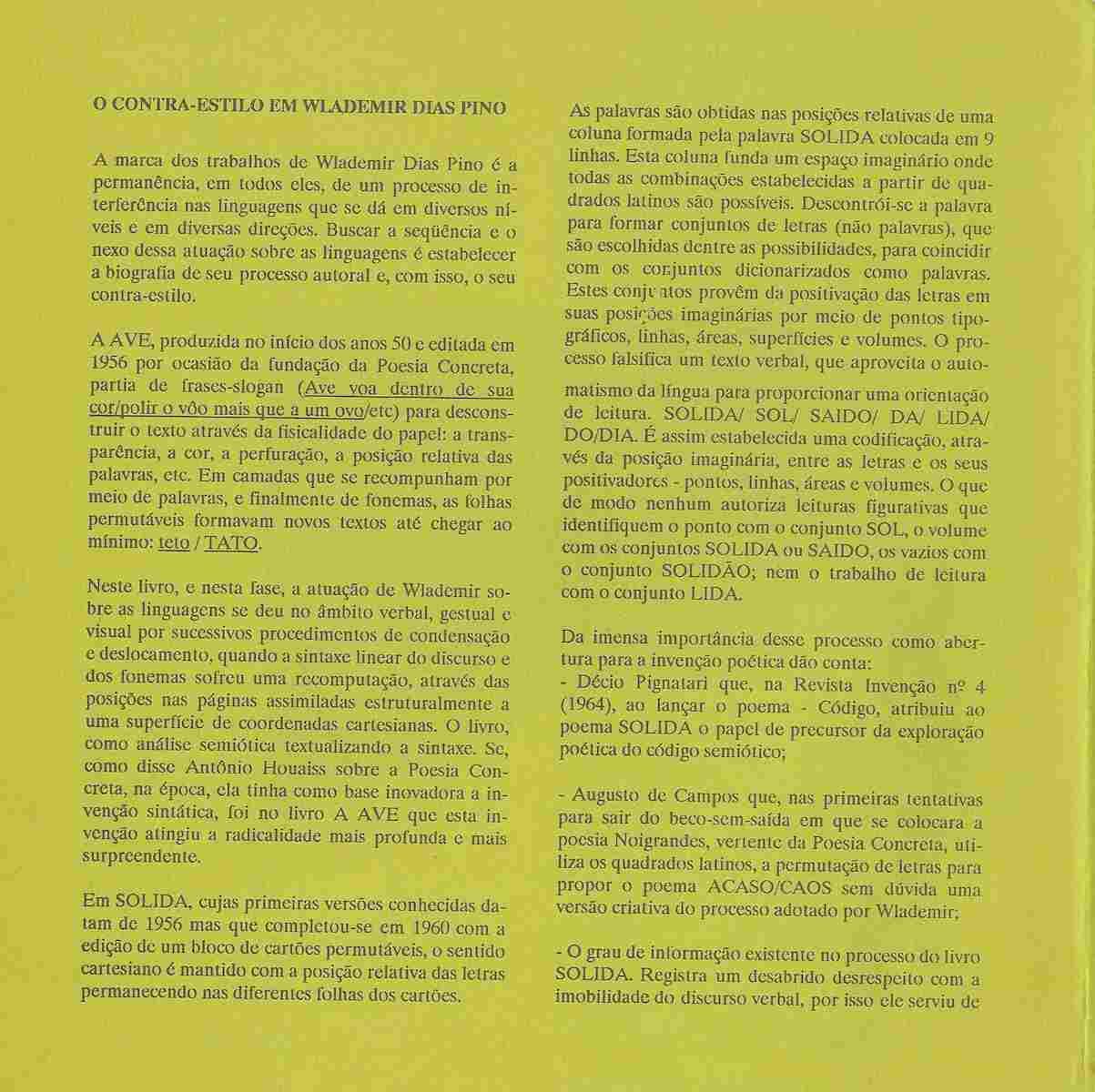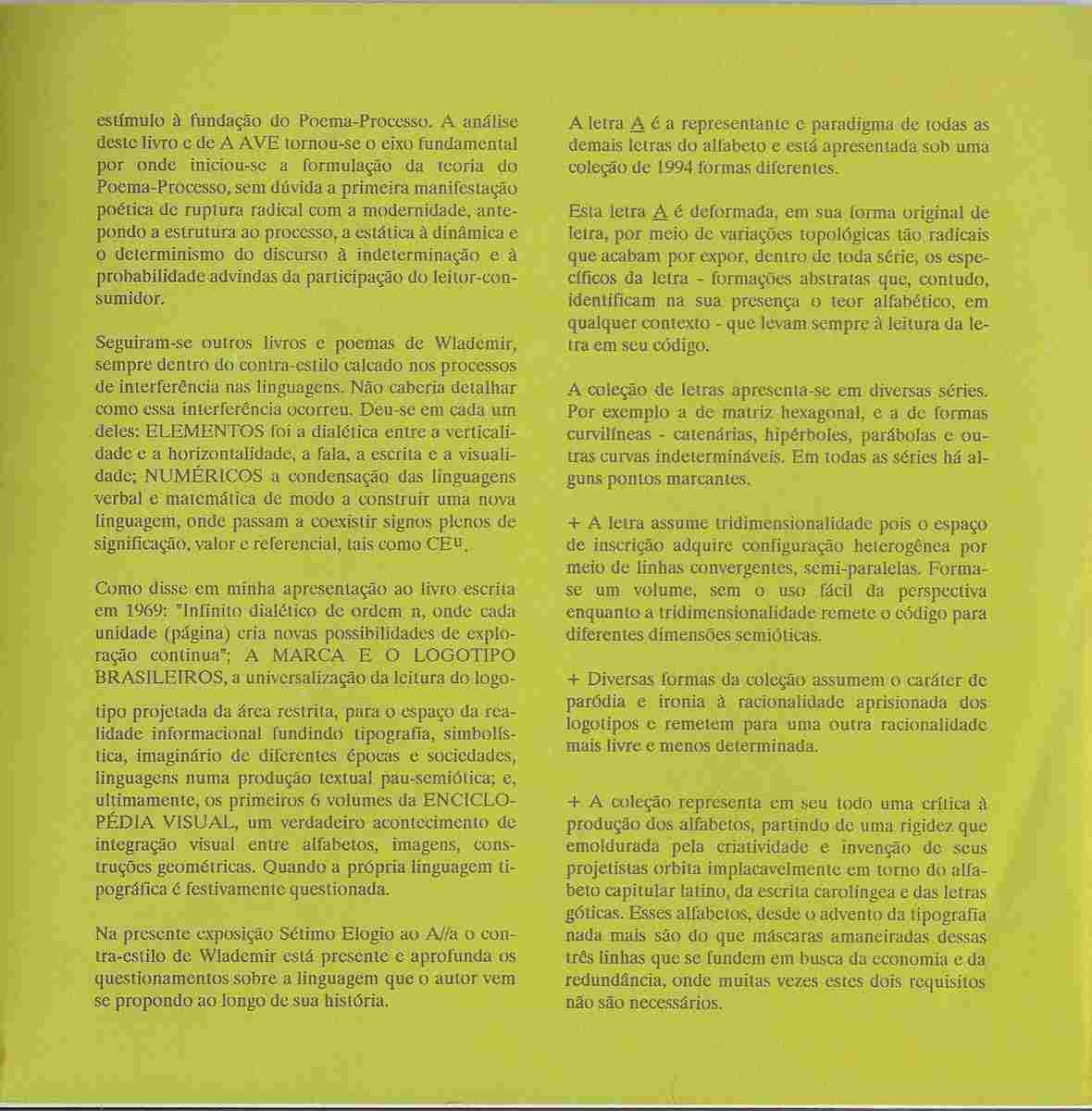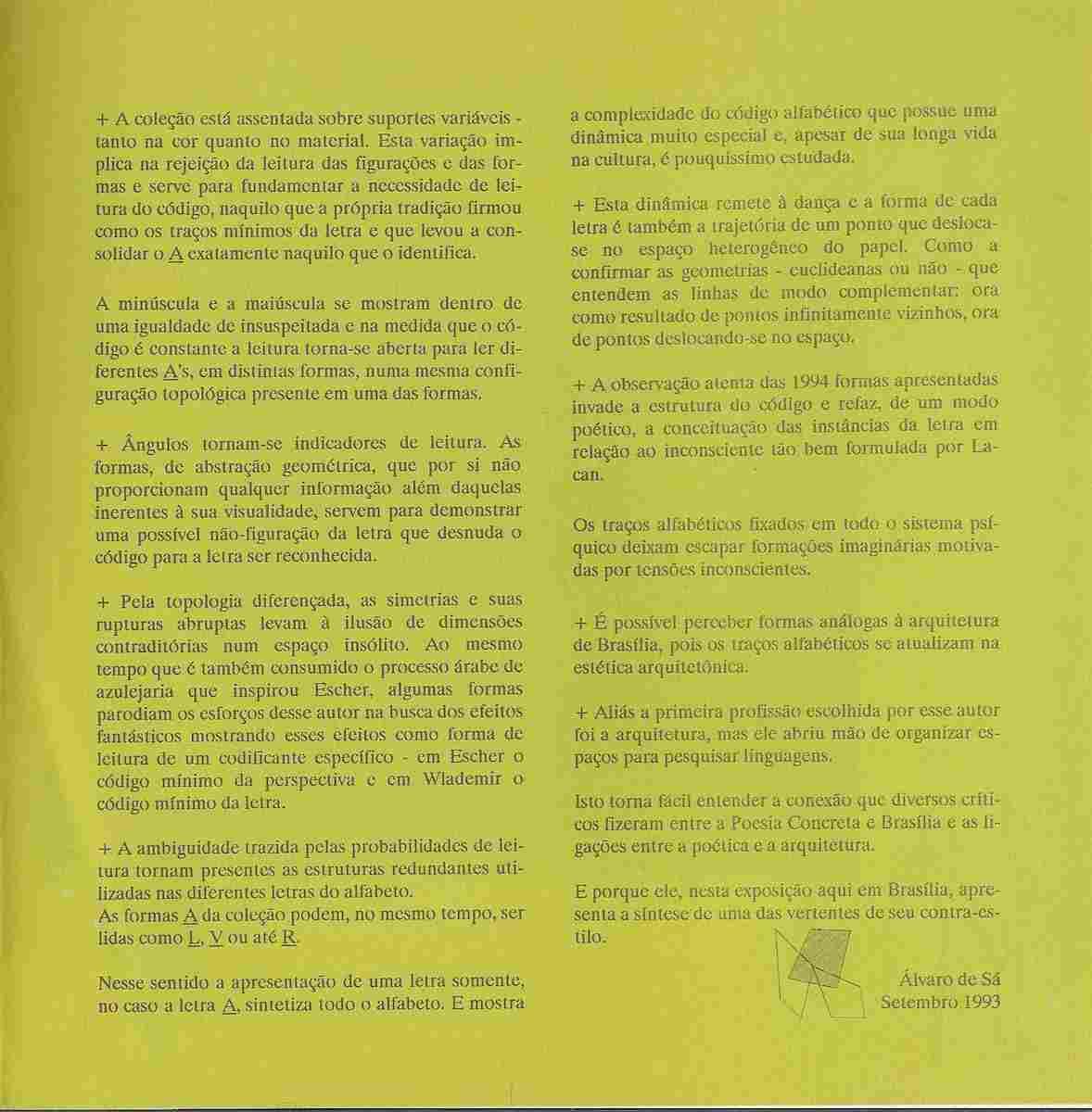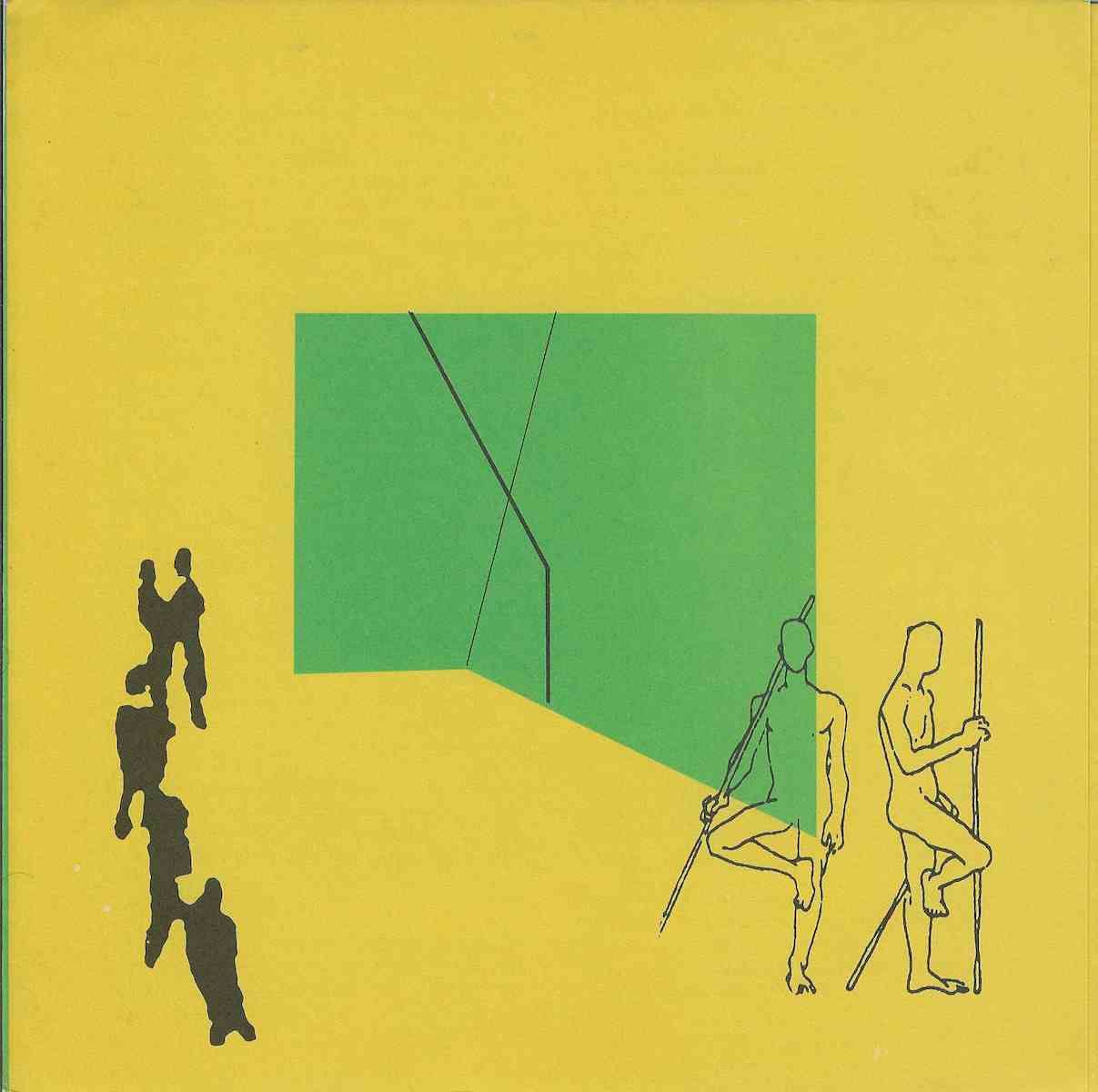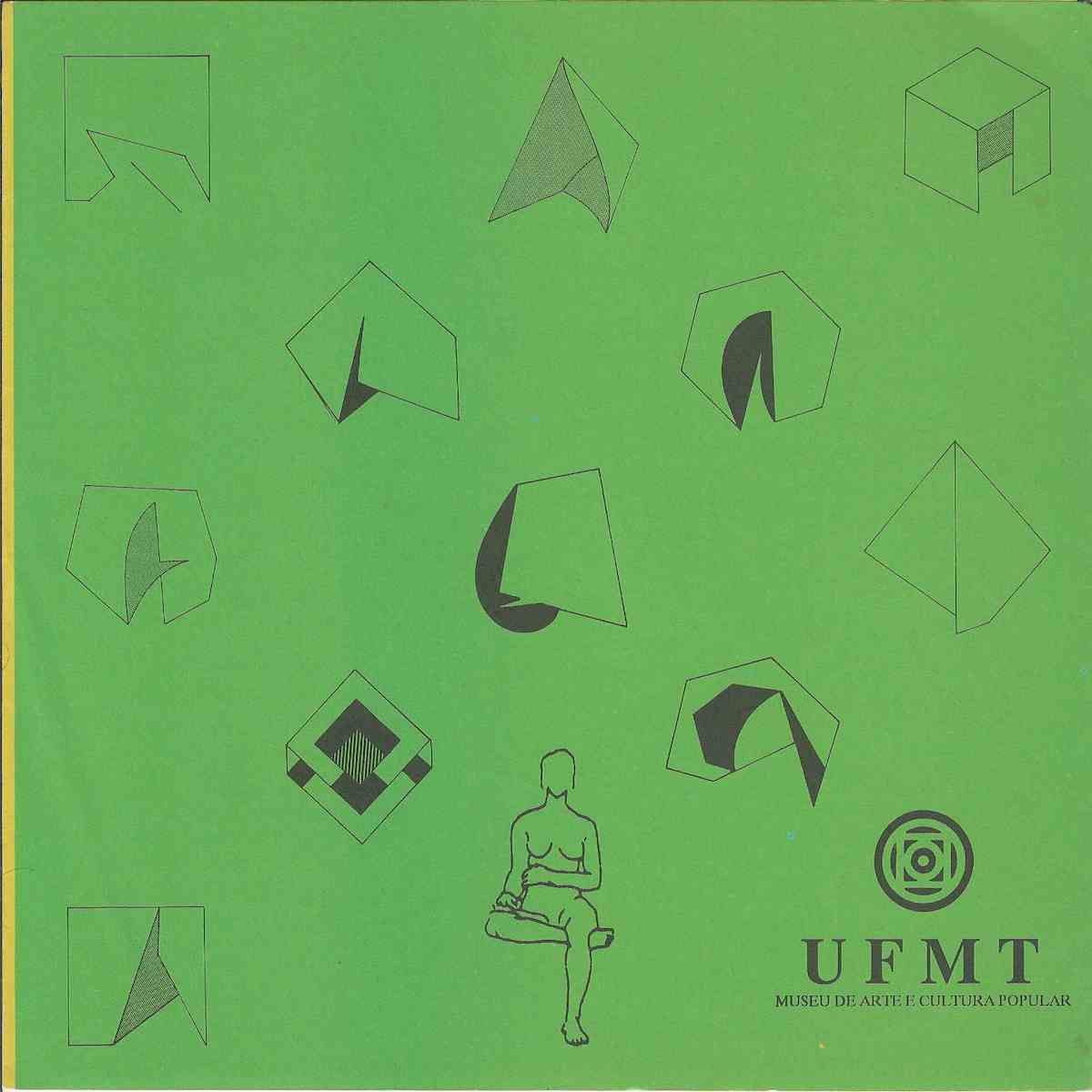
Wlademir Dias Pino, O Contraestilo em Wlademir Dias Pino, setembro de 1993. Conjunto documental e gráfico relacionado às pesquisas de Wlademir Dias Pino sobre poesia visual, linguagem, alfabeto, tipografia, semiótica, espaço, arquitetura e transformação da letra.
Wlademir Dias Pino
Texto para o programa SalsaWlademir Dias Pino, O Contraestilo em Wlademir Dias Pino, setembro de 1993. Conjunto documental e gráfico relacionado às pesquisas de Wlademir Dias Pino sobre poesia visual, linguagem, alfabeto, tipografia, semiótica, espaço, arquitetura e transformação da letra. O núcleo teórico do material é um ensaio de Álvaro de Sá, assinado em setembro de 1993, no qual o autor examina a trajetória de Wlademir Dias Pino a partir do conceito de contraestilo. O conjunto inclui ainda estudos gráficos e espaciais da letra A, figuras humanas, estruturas geométricas e a identificação institucional da UFMT e do Museu de Arte e Cultura Popular.Álvaro de Sá inicia o ensaio afirmando que uma característica permanente dos trabalhos de Wlademir Dias Pino é o processo de interferência nas linguagens, realizado em diferentes níveis e direções. Para o autor, acompanhar essa sequência de interferências permite estabelecer uma biografia do processo autoral de Wlademir e, simultaneamente, compreender a formação de seu contraestilo. Assim, a produção de Wlademir Dias Pino não é apresentada como repetição de uma fórmula visual estável, mas como permanente investigação e transformação dos sistemas de linguagem.O texto dedica atenção especial a A Ave, produzida no início da década de 1950 e editada em 1956. Segundo Álvaro de Sá, o livro parte de frases e estruturas verbais para progressivamente desconstruir o texto por meio da fisicalidade do papel, da transparência, da cor, da perfuração, da posição relativa das palavras e da sobreposição de diferentes camadas. As folhas permutáveis recompõem novos textos e conduzem a obra em direção a unidades cada vez menores, chegando aos fonemas e a relações mínimas entre elementos verbais e sensoriais.A Ave é apresentada como uma experiência na qual a linguagem verbal, gestual e visual é submetida a sucessivos procedimentos de condensação e deslocamento. A sintaxe linear do discurso e dos fonemas sofre uma recomputação através da disposição espacial das páginas, assimiladas a uma superfície de coordenadas cartesianas. Álvaro de Sá aproxima esse procedimento de uma análise semiótica que transforma a própria sintaxe em objeto de investigação.O ensaio menciona Antônio Houaiss e sua avaliação da inovação sintática da Poesia Concreta, observando que A Ave teria levado essa investigação a uma radicalidade ainda mais profunda. O documento insere, portanto, o livro de Wlademir Dias Pino no centro das discussões sobre poesia concreta, poesia visual e transformação da sintaxe poética na segunda metade do século XX.Outro trabalho fundamental analisado é SOLIDA. Segundo o ensaio, suas primeiras versões conhecidas datam de 1956 e o projeto teria sido completado em 1960 com a edição de um bloco de cartões permutáveis. O sentido cartesiano permanece através da posição relativa das letras distribuídas pelas diferentes folhas ou cartões.Em SOLIDA, palavras são obtidas a partir das posições relativas de uma coluna formada pela palavra SOLIDA disposta em diferentes linhas. A estrutura cria um espaço imaginário no qual diversas combinações derivadas de quadrados latinos podem ser realizadas. O processo desconstrói a palavra para produzir conjuntos de letras e não necessariamente palavras convencionais. Esses conjuntos são selecionados entre as possibilidades combinatórias e podem coincidir com formas reconhecidas pelo dicionário.Segundo Álvaro de Sá, esses conjuntos derivam do posicionamento das letras em relações imaginárias estabelecidas por pontos tipográficos, linhas, áreas, superfícies e volumes. O processo constrói uma espécie de texto verbal transformado, aproveitando o automatismo da língua para oferecer uma orientação de leitura sem restringir a experiência a uma única interpretação.O ensaio cita sequências derivadas de SOLIDA e explica que o método estabelece uma codificação através da posição imaginária das letras e de seus elementos estruturais. Ao mesmo tempo, o autor alerta que isso não autoriza uma leitura simplesmente figurativa. Um ponto não deve ser automaticamente identificado com determinado conjunto verbal, nem um volume com outro. A operação fundamental encontra se no funcionamento do sistema e na mobilidade das possibilidades de leitura.Álvaro de Sá destaca a importância desse processo para a invenção poética e recorda a recepção de SOLIDA no contexto da poesia experimental brasileira. O texto menciona Décio Pignatari e a revista Invenção número 4, de 1964, registrando que Pignatari, ao apresentar o poema Código, atribuiu a SOLIDA um papel precursor na exploração poética do código semiótico.O ensaio também menciona Augusto de Campos. Segundo Álvaro de Sá, experiências de permutação de letras desenvolvidas por Augusto de Campos para o poema ACASO CAOS poderiam ser relacionadas criativamente ao procedimento anteriormente desenvolvido por Wlademir Dias Pino em SOLIDA. A comparação situa a obra dentro de um campo mais amplo de poesia combinatória, permutacional e semiótica.Para Álvaro de Sá, o nível de informação contido no processo de SOLIDA representa uma ruptura com a imobilidade do discurso verbal e teria contribuído para o caminho que desembocaria na formulação teórica do Poema Processo. A análise de A Ave e SOLIDA é apresentada como eixo fundamental para compreender a passagem da escritura ao processo, do estático ao dinâmico, do determinismo à indeterminação e à participação ativa do leitor consumidor.O texto estabelece dessa forma uma genealogia direta entre as pesquisas de Wlademir Dias Pino realizadas nas décadas de 1950 e 1960 e o surgimento do Poema Processo. A obra deixa de ser entendida apenas como objeto verbal concluído e passa a ser concebida como sistema aberto, procedimento, matriz de possibilidades e experiência de participação.Álvaro de Sá menciona outros livros e projetos de Wlademir Dias Pino que continuaram essa interferência nas linguagens. ELEMENTOS é associado à dialética entre verticalidade e horizontalidade e às relações entre fala, escrita e visualidade. NUMÉRICOS é relacionado à condensação das linguagens verbal e matemática, construindo uma nova linguagem na qual podem coexistir signos dotados de significado, valor e referência.O texto recupera ainda uma apresentação realizada por Álvaro de Sá ao livro Escrita em 1969, na qual destacava a estrutura dialética da página como unidade capaz de gerar novas possibilidades contínuas de exploração.Entre outras etapas da trajetória de Wlademir Dias Pino, o ensaio menciona A MARCA E O LOGOTIPO BRASILEIROS, associando o projeto à universalização da leitura do logotipo e ao estudo da realidade informacional. A pesquisa reúne tipografia, simbologia e imaginário de diferentes épocas e sociedades em uma produção textual e semiótica.Também são citados os seis primeiros volumes da ENCICLOPÉDIA VISUAL, apresentados como acontecimento de integração entre alfabetos, imagens e construções geométricas. Nesse conjunto, a própria linguagem tipográfica passa a ser sistematicamente interrogada.Essas diferentes experiências convergem na exposição identificada no texto como Sétimo Elogio ao A/a. Álvaro de Sá afirma que o contraestilo de Wlademir está presente nessa exposição e aprofunda questionamentos sobre a linguagem que o artista vinha desenvolvendo ao longo de sua trajetória.A letra A é escolhida como representante e paradigma das demais letras do alfabeto e, segundo o ensaio, é apresentada sob uma coleção de formas diferentes. O A deixa de ser apenas caractere tipográfico e passa a constituir uma matriz de variações topológicas, espaciais e semióticas.A letra é deformada a partir de sua configuração original por variações topológicas não radicais que acabam expondo diferentes aspectos de sua estrutura. Mesmo quando as formas se tornam abstratas, elas mantêm sinais suficientes para permitir o reconhecimento de um conteúdo alfabético e conduzir novamente à leitura da letra dentro do código.A coleção apresenta diferentes séries. O texto menciona, entre elas, uma matriz hexagonal e séries de formas curvilíneas, incluindo catenárias, hipérboles, parábolas e outras curvas de desenvolvimento potencialmente indeterminado.Álvaro de Sá destaca que a letra adquire tridimensionalidade. O espaço de inscrição passa a assumir uma configuração heterogênea através de linhas convergentes e não paralelas. Forma se um volume sem recorrer ao uso fácil da perspectiva, ao mesmo tempo em que a tridimensionalidade transporta o código para diferentes dimensões semióticas.A coleção possui também dimensão de paródia e ironia em relação à racionalidade rígida dos logotipos. Para o autor, determinadas formas remetem a uma racionalidade mais livre e menos determinada. A pesquisa deixa de ser apenas tipográfica e se transforma em crítica aos mecanismos históricos de padronização do alfabeto.Álvaro de Sá observa que a produção dos alfabetos esteve cercada, ao longo do tempo, por uma rigidez ligada à escrita carolíngia e às letras góticas. Em sua interpretação, muitos desses alfabetos representam máscaras estilizadas das linhas fundamentais que constituem as letras, e a pesquisa de Wlademir procura revelar as estruturas mínimas existentes por trás dessas convenções.Outro aspecto importante é a utilização de suportes variáveis, tanto em cor quanto em material. A variação rejeita a ideia da letra como configuração fixa e demonstra a necessidade de releitura do código alfabético. O texto chama atenção para o fato de que a tradição consolidou determinados traços mínimos como elementos suficientes para reconhecer uma letra, especialmente o A, e Wlademir explora exatamente os limites dessa identificação.As versões maiúscula e minúscula da letra são colocadas em relação dinâmica. À medida que o código se abre, a leitura pode reconhecer diferentes As dentro de uma mesma configuração topológica.Algumas formas funcionam como indicadores de leitura. Outras tornam se abstrações geométricas que oferecem inicialmente informações apenas visuais, provocando uma situação de não figuração da letra antes que o código volte a ser reconhecido. Essa tensão entre reconhecimento e estranhamento é central no processo.O ensaio aproxima as construções de Wlademir de certos princípios encontrados na obra de M C Escher e na tradição da azulejaria árabe. Álvaro de Sá ressalta, porém, que existem diferenças essenciais. Em Escher, o elemento mínimo estaria relacionado ao código da perspectiva, enquanto em Wlademir Dias Pino o código mínimo seria a própria letra.A diferenciação topológica e a ruptura de simetrias criam ilusões espaciais e dimensões contraditórias. O alfabeto passa assim a atuar como uma arquitetura de possibilidades perceptivas.As ambiguidades de leitura também fazem com que uma única estrutura possa sugerir diferentes letras. O texto menciona que determinadas formas do A podem simultaneamente ser percebidas como L, V ou até R. A apresentação de uma única letra permite, dessa maneira, sintetizar potencialmente todo o alfabeto.Para Álvaro de Sá, esse procedimento demonstra a complexidade do código alfabético, um sistema dotado de dinâmica particular que, apesar de sua longa presença cultural, ainda seria pouco estudado em sua dimensão visual e estrutural.Essa dinâmica começa a produzir uma espécie de dança das formas. Cada letra corresponde também à trajetória de um ponto deslocando se no espaço heterogêneo do papel. A pesquisa aproxima geometria, movimento, código e percepção.O ensaio observa ainda que as formas apresentadas em 1994 invadem a estrutura do código e permitem uma reflexão poética sobre as relações entre a letra e o inconsciente. Os traços alfabéticos estabilizados dentro do sistema psíquico podem liberar formações imaginárias motivadas por tensões inconscientes.Álvaro de Sá estabelece também uma aproximação entre as formas da pesquisa de Wlademir e a arquitetura de Brasília. Segundo o texto, os traços alfabéticos podem atualizar se dentro da estética arquitetônica. Essa relação entre letra e construção espacial adquire particular importância porque a arquitetura foi uma das práticas profissionais escolhidas por Wlademir Dias Pino e lhe permitiu organizar espaços para investigar linguagens.O ensaio conclui que essa relação ajuda a compreender as conexões apontadas por diversos críticos entre Poesia Concreta e Brasília e entre poética e arquitetura. A exposição realizada em Brasília é apresentada, portanto, como síntese de uma das vertentes do contraestilo de Wlademir Dias Pino.As imagens que acompanham o texto reforçam essa dimensão espacial. Em uma composição, figuras humanas aparecem ao redor de um grande plano verde colocado sobre um campo amarelo, atravessado por linhas que sugerem eixo, profundidade, deslocamento e estrutura. Em outra página, diferentes configurações geométricas e curvilíneas são distribuídas sobre um fundo verde, apresentando variações que podem ser interpretadas simultaneamente como letra, objeto, planta, volume, arquitetura e escultura. A presença da figura humana estabelece escala e sugere o deslocamento da letra do espaço gráfico para o espaço corporal e ambiental.O Contraestilo em Wlademir Dias Pino constitui um documento crítico de grande relevância porque oferece uma interpretação histórica e conceitual da obra de Wlademir Dias Pino escrita por Álvaro de Sá, outro protagonista fundamental do Poema Processo. O texto documenta relações entre A Ave, SOLIDA, ELEMENTOS, NUMÉRICOS, Escrita, A Marca e o Logotipo Brasileiros, Enciclopédia Visual e a exposição Sétimo Elogio ao A/a, formando uma importante cartografia da produção do artista.O documento é especialmente relevante para pesquisas sobre Wlademir Dias Pino, Álvaro de Sá, Poema Processo, Poesia Concreta, A Ave, SOLIDA, poesia visual brasileira, poesia experimental, semiótica, código alfabético, poesia combinatória, livros permutáveis, livro de artista, tipografia experimental, design gráfico, comunicação visual, alfabetos, logotipos, Enciclopédia Visual, arquitetura, Brasília, M C Escher, Décio Pignatari, Augusto de Campos, Antônio Houaiss, revista Invenção, UFMT, Museu de Arte e Cultura Popular e história da vanguarda brasileira.ENGLISHText for the Salsa programWlademir Dias Pino, The Counterstyle in Wlademir Dias Pino, September 1993. Documentary and graphic ensemble related to the investigations of Wlademir Dias Pino into visual poetry, language, alphabet, typography, semiotics, space, architecture and the transformation of letters. The theoretical core of the material is an essay by Álvaro de Sá, signed in September 1993, in which he examines the trajectory of Wlademir Dias Pino through the concept of counterstyle. The ensemble also contains graphic and spatial studies of the letter A, human figures, geometric structures and the institutional identification of UFMT and the Museum of Popular Art and Culture.Álvaro de Sá begins by stating that a permanent characteristic of the work of Wlademir Dias Pino is a process of interference within languages, operating at different levels and in different directions. For the author, following this sequence of interventions makes it possible to establish a biography of the creative process of Wlademir and, simultaneously, to understand the formation of his counterstyle. His production is therefore presented not as the repetition of a stable visual formula but as a continuous investigation and transformation of systems of language.The essay gives particular attention to A Ave, produced in the early 1950s and published in 1956. According to Álvaro de Sá, the book begins with verbal phrases and structures and progressively dismantles the text through the physical properties of paper, transparency, color, perforation, the relative position of words and the superimposition of layers. Permutable sheets reconstruct new texts and lead the work toward increasingly reduced units, eventually reaching phonemes and minimal relationships between verbal and sensory components.A Ave is presented as an experiment in which verbal, gestural and visual language is subjected to successive procedures of condensation and displacement. The linear syntax of discourse and phonemes undergoes a recomputation through the spatial arrangement of pages conceived as a surface of Cartesian coordinates. Álvaro de Sá relates this procedure to a semiotic analysis in which syntax itself becomes the object of investigation.The essay refers to Antônio Houaiss and his assessment of the syntactic innovations of Concrete Poetry, arguing that A Ave carried this investigation toward an even more radical territory. The document consequently places the book by Wlademir Dias Pino at the center of discussions concerning Concrete Poetry, visual poetry and the transformation of poetic syntax during the second half of the twentieth century.Another fundamental work analyzed in the essay is SOLIDA. According to the text, its earliest known versions date from 1956 and the project was completed in 1960 with the publication of a block of permutable cards. A Cartesian principle is maintained through the relative position of letters distributed across the different cards.In SOLIDA, words are generated from the relative positions of a column formed by the word SOLIDA distributed over different lines. This column establishes an imaginary space in which combinations derived from Latin squares become possible. The procedure decomposes the word in order to create sets of letters that are not necessarily conventional words. These sets are selected from the available combinatorial possibilities and may coincide with forms recognized by dictionaries.According to Álvaro de Sá, these combinations derive from the positioning of letters within imaginary relationships constructed through typographic points, lines, areas, surfaces and volumes. The process produces a transformed verbal text that uses the automatic mechanisms of language to suggest orientations of reading without limiting the experience to a single interpretation.The essay explains that the method establishes a codification based on the imaginary positions of letters and their structural elements. At the same time, Álvaro de Sá warns that the system does not authorize a merely figurative reading. A point should not automatically be identified with a particular verbal set, nor should a volume be equated with another set. The essential operation lies in the functioning of the system and in the mobility of possible readings.Álvaro de Sá emphasizes the importance of this process for poetic invention and recalls the reception of SOLIDA within Brazilian experimental poetry. The essay mentions Décio Pignatari and issue number 4 of the magazine Invenção from 1964, recording that Pignatari, when presenting the poem Código, attributed to SOLIDA a pioneering role in the poetic exploration of the semiotic code.The text also refers to Augusto de Campos. According to Álvaro de Sá, experiments with letter permutations developed by Augusto de Campos for the poem ACASO CAOS can be creatively related to procedures previously explored by Wlademir Dias Pino in SOLIDA. This comparison situates the work within a broader field of combinatorial, permutational and semiotic poetry.For Álvaro de Sá, the degree of information contained in the process of SOLIDA represents a challenge to the immobility of verbal discourse and contributed to the path that would lead to the theoretical formulation of Poema Processo. The analysis of A Ave and SOLIDA is presented as fundamental to understanding the movement from writing to process, from the static to the dynamic, from determinism to indeterminacy and to the active participation of the reader consumer.The essay therefore establishes a direct genealogy between the investigations undertaken by Wlademir Dias Pino during the 1950s and 1960s and the emergence of Poema Processo. The work ceases to be understood merely as a completed verbal object and becomes an open system, a procedure, a matrix of possibilities and an experience of participation.Álvaro de Sá refers to other books and projects by Wlademir Dias Pino that continued this interference within languages. ELEMENTOS is associated with the dialectic between verticality and horizontality and with relationships among speech, writing and visuality. NUMÉRICOS is connected with the condensation of verbal and mathematical languages and the creation of a new language in which signs endowed with meaning, value and reference can coexist.The essay also recalls an introduction written by Álvaro de Sá for the book Escrita in 1969, in which he emphasized the dialectical structure of the page as a unit capable of creating continuous new possibilities of exploration.Among other phases of the work of Wlademir Dias Pino, the essay mentions A MARCA E O LOGOTIPO BRASILEIROS, connecting the project with the universalization of logo reading and the study of informational reality. The research combines typography, symbolic systems and the imaginary of different historical periods and societies within a textual and semiotic production.The first six volumes of ENCICLOPÉDIA VISUAL are also cited and described as an important development in the visual integration of alphabets, images and geometric constructions. In this project, typographic language itself becomes systematically questioned.These different experiences converge in the exhibition identified in the text as Sétimo Elogio ao A/a. Álvaro de Sá states that the counterstyle of Wlademir is present in the exhibition and intensifies the questions about language that the artist had developed throughout his career.The letter A is selected as representative and paradigm of the other letters of the alphabet and appears through a collection of different forms. The A ceases to function merely as a typographic character and becomes a matrix of topological, spatial and semiotic variations.The letter is deformed from its original structure through topological variations that expose different aspects of its configuration. Even when the resulting formations become abstract, they retain enough information to permit recognition of their alphabetic character and eventually lead the viewer back to the reading of the letter within its code.The collection includes different series. The essay mentions a hexagonal matrix and series based on curvilinear forms including catenaries, hyperbolas, parabolas and other potentially indeterminate curves.Álvaro de Sá emphasizes that the letter acquires three dimensionality. The field of inscription becomes heterogeneous through converging and nonparallel lines. A volume emerges without dependence on conventional perspective, while three dimensionality carries the code into different semiotic dimensions.The collection also incorporates parody and irony toward the rigid rationality associated with logos. Some forms refer to a freer and less determined rationality. The investigation therefore goes beyond typography and becomes a critique of historical mechanisms used to standardize alphabets.Álvaro de Sá observes that the production of alphabets has historically been surrounded by forms of rigidity associated with Carolingian writing and Gothic letters. In his interpretation, many alphabets are stylized masks of the fundamental lines that constitute letters, while the research of Wlademir seeks to expose the minimal structures hidden behind those conventions.Another important aspect is the use of variable supports in both color and material. Variation rejects the concept of the letter as a fixed configuration and reinforces the need to reread the alphabetic code. The essay draws attention to the fact that tradition has established certain minimal strokes as sufficient elements for identifying a letter, particularly the A, and Wlademir investigates the limits of precisely this recognition.Uppercase and lowercase forms are brought into a dynamic relationship. As the code becomes open, reading can recognize different forms of A within the same topological configuration.Some shapes function as indicators of reading. Others become geometric abstractions that initially offer information only through visual perception, demonstrating a possible state of nonfiguration before the alphabetic code is recognized again. This tension between recognition and estrangement is central to the process.The essay relates the constructions of Wlademir to certain principles found in the work of M C Escher and in the tradition of Arab tile patterns. Álvaro de Sá nevertheless stresses important differences. In Escher the minimum code is associated with perspective, while in Wlademir Dias Pino the minimum code is the letter itself.Topological differentiation and abrupt breaks in symmetry produce spatial illusions and contradictory dimensions. The alphabet therefore begins to operate as an architecture of perceptual possibilities.Ambiguities of reading also allow one structure to suggest several different letters. The essay states that certain variations of A can simultaneously be read as L, V or even R. In this sense, the presentation of a single letter can potentially synthesize the entire alphabet.For Álvaro de Sá, this procedure demonstrates the complexity of the alphabetic code, a system with a distinctive internal dynamic that, despite its long cultural history, has received surprisingly little study in its visual and structural dimensions.This dynamic begins to resemble a dance of forms. Each letter can also be understood as the trajectory of a point moving through the heterogeneous space of the page. The investigation thus brings together geometry, movement, code and perception.The essay further observes that the forms presented in 1994 enter into the structure of the code and enable a poetic reflection on the relationship between letters and the unconscious. Alphabetic traces fixed within the psychic system may release imaginary formations generated by unconscious tensions.Álvaro de Sá also establishes a relationship between these forms and the architecture of Brasília. According to the text, alphabetic traces can become actualized within architectural aesthetics. This relationship between letter and spatial construction is especially significant because architecture was among the professional practices selected by Wlademir Dias Pino and enabled him to organize spaces for the investigation of languages.The essay concludes that this relationship helps explain connections made by critics between Concrete Poetry and Brasília and between poetics and architecture. The exhibition in Brasília is consequently presented as a synthesis of one of the principal dimensions of the counterstyle of Wlademir Dias Pino.The images accompanying the essay reinforce this spatial dimension. One composition shows human figures around a large green plane on a yellow field crossed by lines suggesting axes, depth, displacement and structure. Another page distributes different geometric and curvilinear configurations across a green background, presenting variations that can simultaneously be interpreted as letters, objects, plans, volumes, architecture and sculpture. Human figures establish scale and suggest the displacement of the letter from graphic space into bodily and environmental space.The Counterstyle in Wlademir Dias Pino is an important critical document because it provides a historical and conceptual interpretation of the work of Wlademir Dias Pino written by Álvaro de Sá, another fundamental figure of Poema Processo. The essay documents relationships among A Ave, SOLIDA, ELEMENTOS, NUMÉRICOS, Escrita, A Marca e o Logotipo Brasileiros, Enciclopédia Visual and the exhibition Sétimo Elogio ao A/a, creating an important map of the intellectual and artistic production of Wlademir Dias Pino.The document is particularly relevant for research on Wlademir Dias Pino, Álvaro de Sá, Poema Processo, Concrete Poetry, A Ave, SOLIDA, Brazilian visual poetry, experimental poetry, semiotics, alphabetic code, combinatorial poetry, permutable books, artist books, experimental typography, graphic design, visual communication, alphabets, logos, Enciclopédia Visual, architecture, Brasília, M C Escher, Décio Pignatari, Augusto de Campos, Antônio Houaiss, the magazine Invenção, UFMT, the Museum of Popular Art and Culture and the history of the Brazilian avant garde.
Texto de observaçãoConjunto documental relacionado a Wlademir Dias Pino contendo o ensaio O Contraestilo em Wlademir Dias Pino, assinado por Álvaro de Sá em setembro de 1993. O material integra texto crítico, estudos da letra A, desenhos geométricos, estruturas espaciais, figuras humanas e identificação da UFMT e do Museu de Arte e Cultura Popular.O ensaio de Álvaro de Sá interpreta a trajetória de Wlademir Dias Pino através do conceito de contraestilo, definido pela continuidade de processos de interferência sobre diferentes linguagens. O texto estabelece uma sequência histórica que inclui A Ave, SOLIDA, ELEMENTOS, NUMÉRICOS, Escrita, A Marca e o Logotipo Brasileiros, Enciclopédia Visual e a exposição Sétimo Elogio ao A/a.A Ave é analisada por seus recursos materiais e estruturais, entre eles transparência, cor, perfuração, posição das palavras, recomposição das páginas e redução progressiva do discurso a componentes mínimos. SOLIDA é apresentada como experiência de permutação, combinatória e construção de um código semiótico baseado nas posições relativas das letras.O documento registra referências a Antônio Houaiss, Décio Pignatari, Augusto de Campos, à revista Invenção número 4 de 1964, ao poema Código e ao poema ACASO CAOS, oferecendo elementos importantes para o estudo das relações entre Wlademir Dias Pino e o campo da poesia experimental brasileira.Álvaro de Sá considera A Ave e SOLIDA fundamentais para a formulação do Poema Processo, especialmente pela passagem da escritura ao processo, do estático ao dinâmico e do determinismo à indeterminação e à participação do leitor.Na exposição analisada, a letra A funciona como matriz de investigação do alfabeto. Diferentes variações topológicas, curvas, linhas, volumes e suportes transformam a letra em objeto visual e espacial. São mencionadas séries baseadas em matriz hexagonal e em curvas como catenárias, hipérboles e parábolas.O texto relaciona ainda a pesquisa de Wlademir Dias Pino à obra de M C Escher, à azulejaria árabe, à história da escrita, à tipografia carolíngia e gótica, ao inconsciente, à arquitetura e à cidade de Brasília. A arquitetura aparece como campo especialmente significativo na trajetória do artista por sua capacidade de organizar espaços destinados à pesquisa das linguagens.As páginas gráficas mostram variações de estruturas que oscilam entre letra, geometria, objeto, escultura e arquitetura. Figuras humanas introduzem relações de escala e sugerem a passagem do signo gráfico para uma dimensão ambiental.Documento de especial importância para catalogação e indexação de Wlademir Dias Pino e Álvaro de Sá e para pesquisas sobre Poema Processo, A Ave, SOLIDA, poesia visual, poesia concreta, semiótica, alfabeto, tipografia experimental, poesia combinatória, livros permutáveis, design gráfico, arquitetura, Brasília, arte conceitual e vanguardas brasileiras.Observation textDocumentary ensemble related to Wlademir Dias Pino containing the essay The Counterstyle in Wlademir Dias Pino, signed by Álvaro de Sá in September 1993. The material combines critical writing, studies of the letter A, geometric drawings, spatial structures, human figures and the identification of UFMT and the Museum of Popular Art and Culture.The essay interprets the trajectory of Wlademir Dias Pino through the concept of counterstyle, defined by the continuity of processes of interference within different languages. The text establishes a historical sequence including A Ave, SOLIDA, ELEMENTOS, NUMÉRICOS, Escrita, A Marca e o Logotipo Brasileiros, Enciclopédia Visual and the exhibition Sétimo Elogio ao A/a.A Ave is analyzed through its material and structural resources, including transparency, color, perforation, the position of words, recombination of pages and the progressive reduction of discourse into minimal components. SOLIDA is presented as an experiment in permutation, combinatorial organization and the construction of a semiotic code based on the relative positions of letters.The document records references to Antônio Houaiss, Décio Pignatari, Augusto de Campos, issue number 4 of the magazine Invenção from 1964, the poem Código and the poem ACASO CAOS, providing important evidence for the study of the relationship between Wlademir Dias Pino and Brazilian experimental poetry.Álvaro de Sá considers A Ave and SOLIDA fundamental to the development of Poema Processo, particularly through the transition from writing to process, from static structures to dynamic systems and from determinism to indeterminacy and reader participation.In the exhibition discussed by the essay, the letter A functions as a matrix for investigating the alphabet. Topological variations, curves, lines, volumes and different supports transform the letter into a visual and spatial object. The text identifies series based on a hexagonal matrix and on curves such as catenaries, hyperbolas and parabolas.The essay further connects the research of Wlademir Dias Pino with M C Escher, Arab tile patterns, the history of writing, Carolingian and Gothic typography, the unconscious, architecture and the city of Brasília. Architecture is presented as an especially significant field within the trajectory of the artist because of its capacity to organize spaces devoted to the investigation of languages.The graphic pages show structural variations oscillating among letter, geometry, object, sculpture and architecture. Human figures introduce relationships of scale and suggest the transition of the graphic sign into an environmental dimension.Historically significant document for the cataloguing and indexing of Wlademir Dias Pino and Álvaro de Sá and for research concerning Poema Processo, A Ave, SOLIDA, visual poetry, Concrete Poetry, semiotics, alphabet, experimental typography, combinatorial poetry, permutable books, graphic design, architecture, Brasília, conceptual art and the Brazilian avant garde.
Wlademir Dias Pino, The Counterstyle in Wlademir Dias Pino, September 1993. Documentary and graphic ensemble related to the investigations of Wlademir Dias Pino into visual poetry, language, alphabet, typography, semiotics, space, architecture and the transformation of letters.